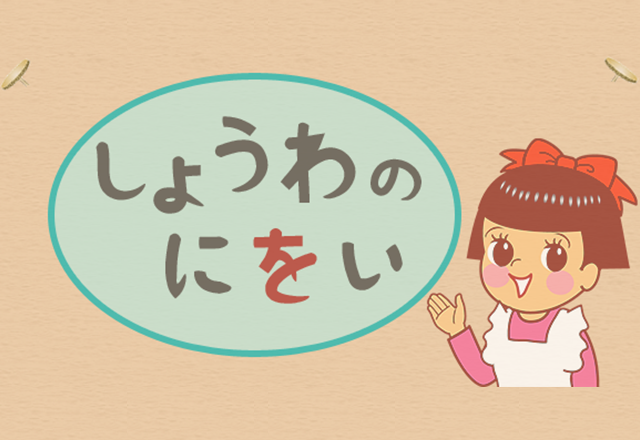
しょうわのにをい 2019.03.24 2016.12.15ショウワノニヲイは、昭和レトロな雰囲気のあるひらがなのフォントです。ライセンス無料で使える商用可のフリーフォントです。ダウンロードしょうわのにをい当サイトはフリーフォントの紹介サイトです。フォントを利用の際には、各サイトで最新の利用条件やライセンスを必ず確認してください。フォント情報ライセンス商用可カテゴリー日本語 > 毛筆体タグ和風、レトロ、懐かしい作者・シリーズふわふわフォント